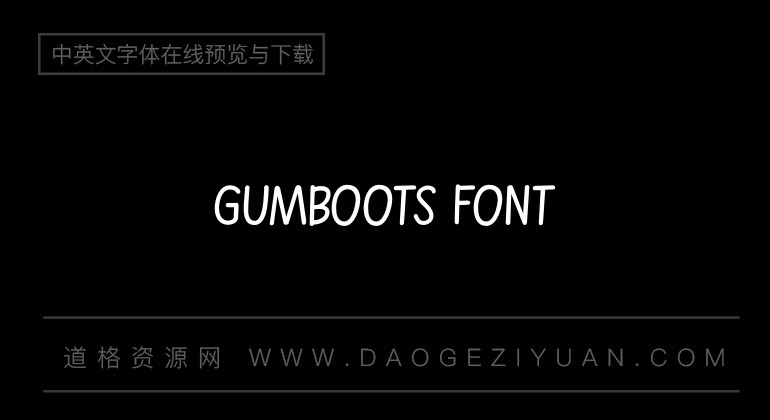
Gumboots Font 是一种非常受欢迎的手写字体,它的特点是非常有趣和富有个性。这种字体设计师是 Jackrabbit Creative,它于2016年发布。 Gumboots Font 有两种版本:一种是正常的字体,另一种是斜体的字体。它的字母非常流畅,每一个字母都有独特的风格和特点。这种字体非常适合用于设计海报、宣传单、贺卡等需要个性化和有趣的场合。 如果您正在寻找一种与众不同的字体设计来增强您的设计作品,那么 Gumboots Font 可能是您需要的字体。它有趣的设计风格将为您的设计作品注入新的生命和活力。内容介绍
Gumboots Font是一款非常不错的手写艺术字体,具有很好的视觉感,适合于文化类的宣传设计、商业类品牌的广告和产品包装设计以及个性化文字排版等较多场景。